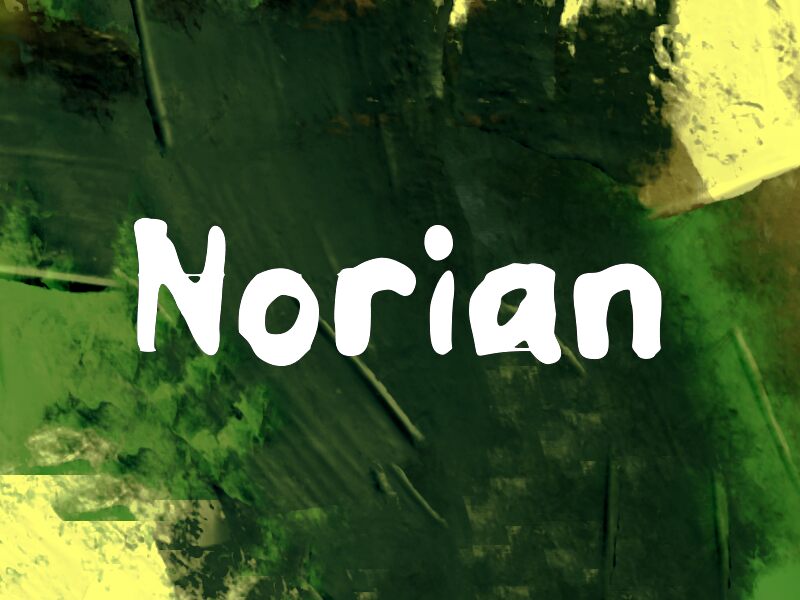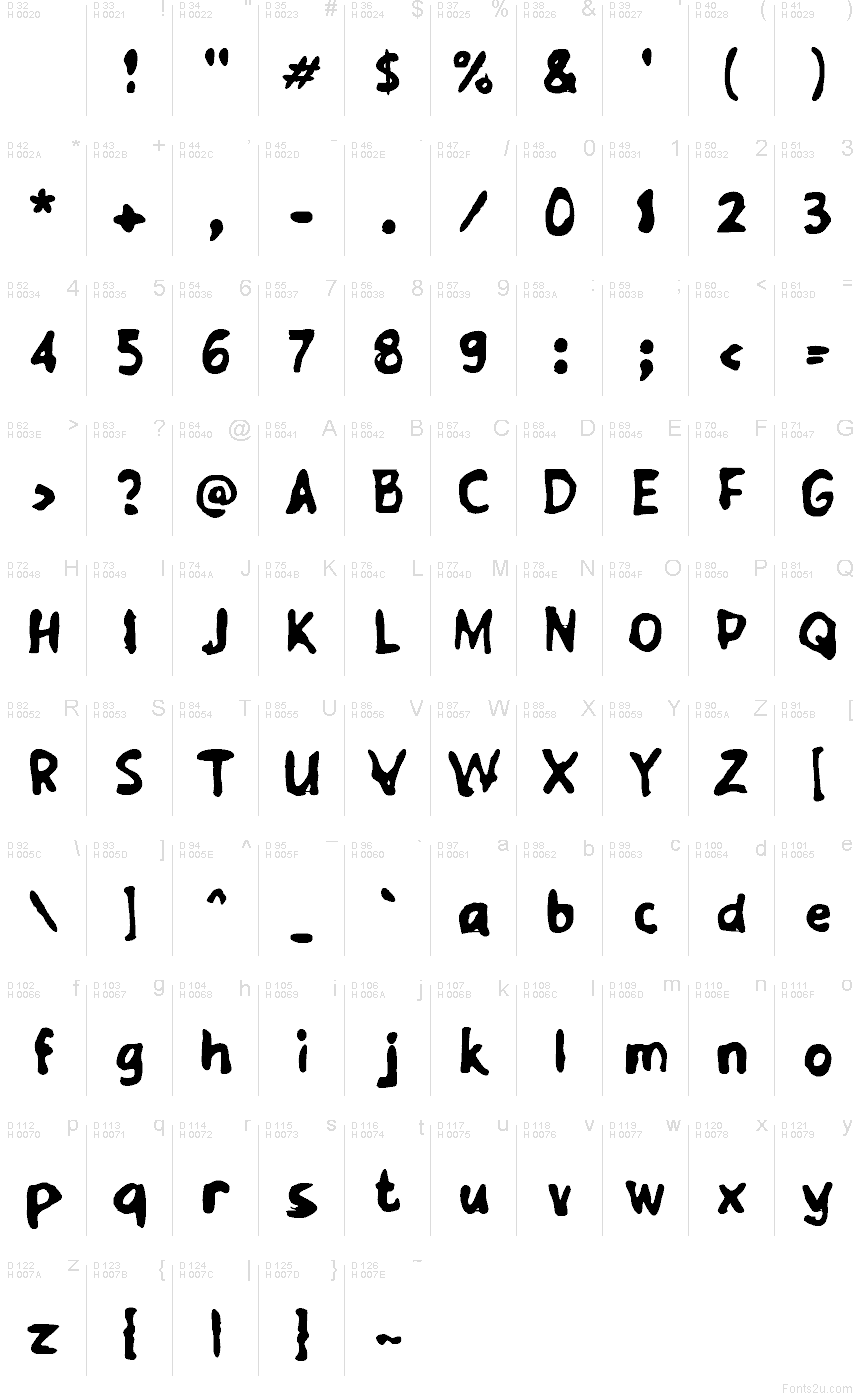
Norian
Norian di Wep è un font brush gratuito, massiccio e dal carattere cartoon dipinto a mano. Le lettere risultano morbide e arrotondate invece che levigate, con tratti pieni, bordi irregolari e spazi interni ampi che mantengono un look casual, amichevole e un po' birichino.
Questo font gratuito è perfetto per titoli di poster, packaging per bambini, branding giocoso, copertine di fanzine e titoli per i social media dove desideri qualcosa di audace ma non rigido. Funziona bene anche per brevi voci di menù o grafiche per eventi, perché il tratto a pennello e le curve morbide danno anche alle parole più semplici una presenza libera e disegnata a mano.